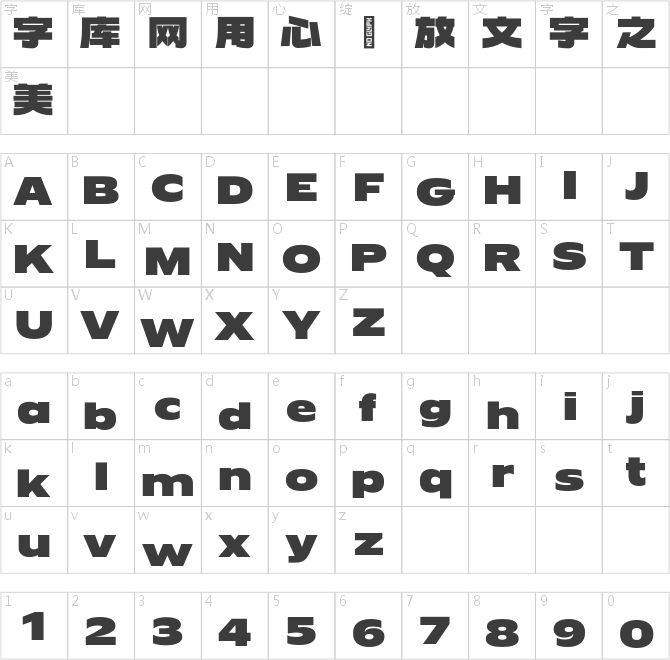
字體名稱: 火山字型 浩海
火山字型 浩海
這是一套極具力量感的標題類字形,輸出兩款風格變化——現代Modern/復古Retro。在文化娛樂、時尚、科技、廣告、視頻制作等領域可作嘗試。 浩海,壓低了字面的高度,中宮大重心中上,沉穩寬闊。極限壓縮字白、字腔、字谷、字距的空間,規整嚴密,字形方整勻稱,章法簡約嚴謹。為統一全套字型風格以及視覺灰度,部份字符作了非常規書寫方式的設計處理。兩款風格呈現出不一樣的視覺氣質,現代款飽滿、簡約、流暢;復古款剛柔相濟個性鮮明。